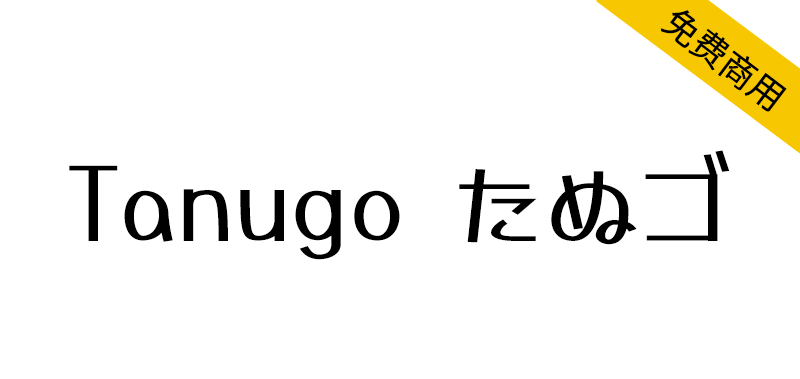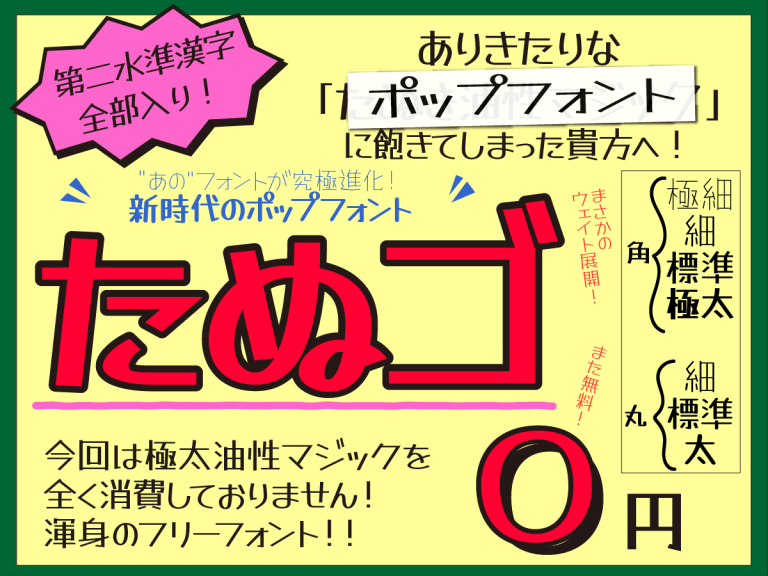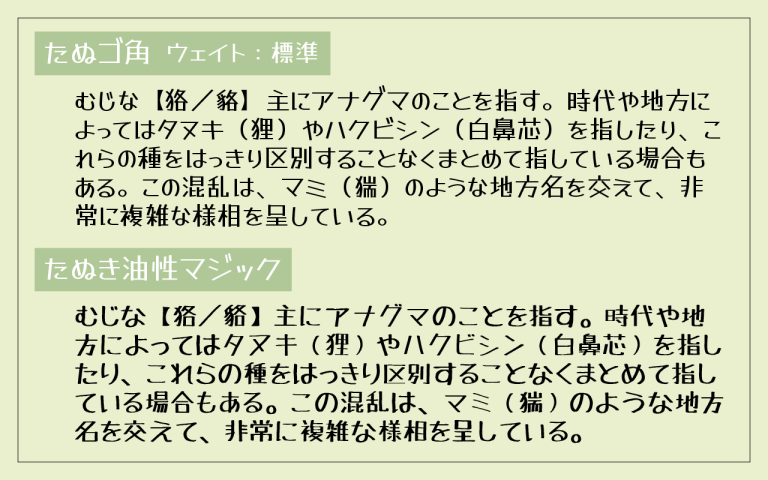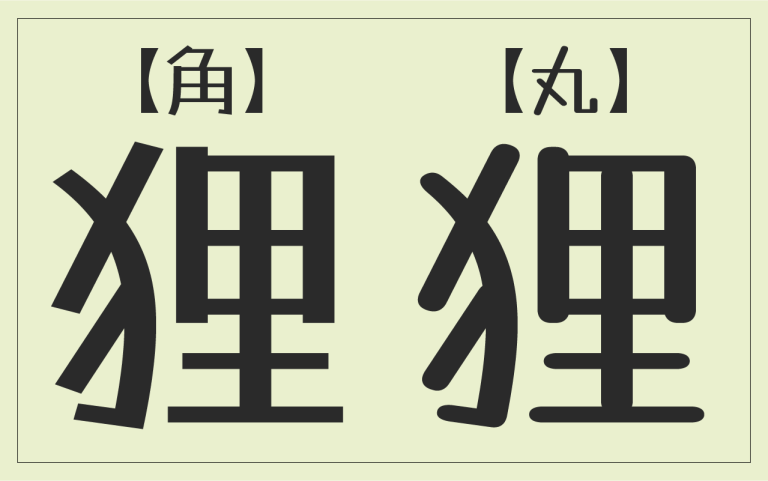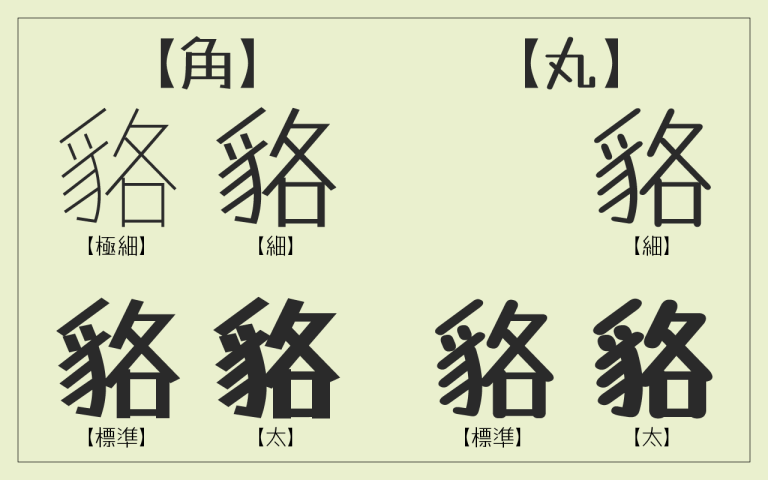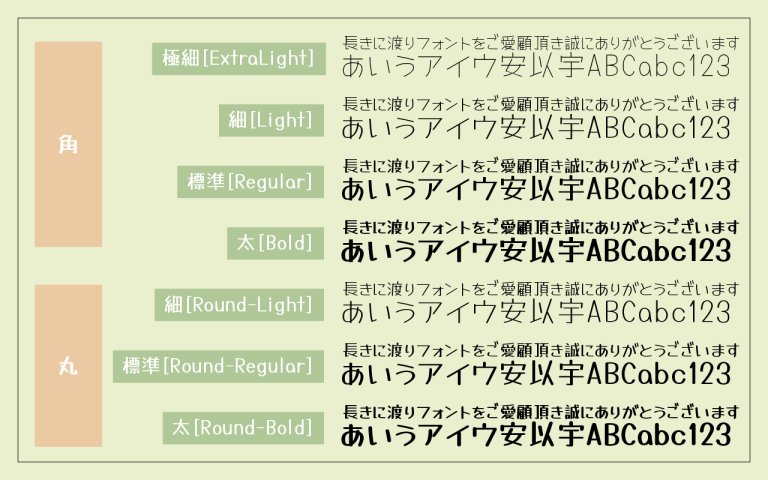
Tanugo(日文名:たぬゴ)是公开的自由字体『たぬき油性マジック』的更新版字体制作的字体,Tanugo手写体保留了『たぬき油性マジック』的特征,保持亲切性的同时,更容易使用、容易阅读,这是一款以可爱的类型设计为目标而制作的字体。
当サイトで公開しているフリーフォント『たぬき油性マジック』のリニューアル版フォントとして作成したフォントです。前作『たぬき油性マジック』の特徴である親しみやすさをキープしつつ、さらに使いやすく・読みやすく、かわいいタイプデザインを目指して作成したフォントです。
Tanugo有两种样式,字体名中带“角”字的字体样式,是硬边的设计。而字体名中带“丸”字的样式,则边角是圆头的设计。
画の端が角張ったデザインの『たぬゴ角』と、丸みを帯びたデザインの『たぬゴ丸』の2種類を用意しました。
另外,Tanugo手写体【角】准备了超细、细、标准、太(ExtraLight·Light、Regular、Bold)的4个字重,Tanugo手写体【丸】准备了细圆、标准丸、太丸(Light·Regular、Bold)3个字重。
また、『たぬゴ角』は極細・細・標準・太(ExtraLight・Light・Regular・Bold)の4ウェイト、『たぬゴ丸』は細丸・標準丸・太丸(Light・Regular・Bold)の3ウェイトを用意しています。